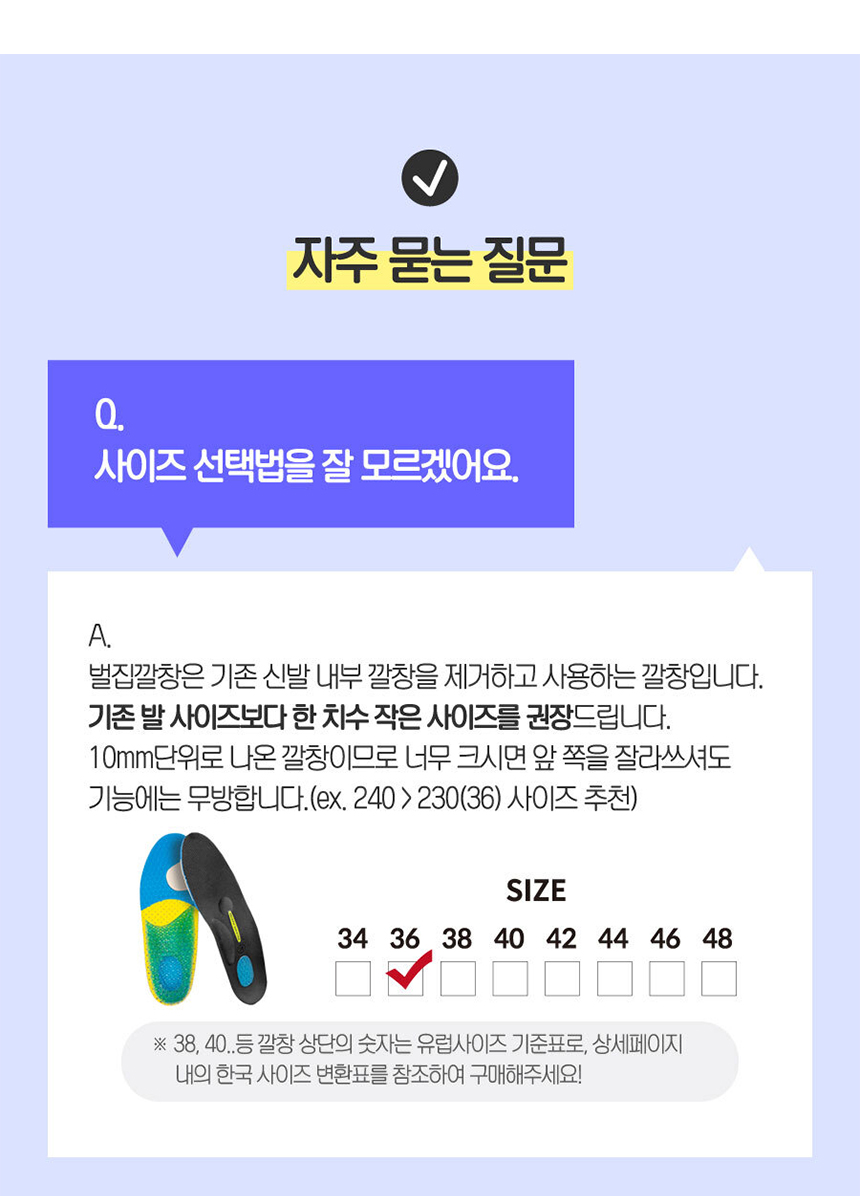
산돌폰트 문의 nin*** 2023.03.21 무슨 폰트 썼는지 확인 부탁드립니다! 댓글 0 등록 sta*** Asia 뉴굴림 같네요. https://www.asiafont.com/asfont/m_view.php?ps_db=sample&ps_boid=237&ps_page=4&ps_sele=&ps_ques=&ps_line=asc&ps_choi=&ps_divi= 장평값을 줘서 가로폭을 좀 줄인 것 같아요 2023-03-21 답글 달기 댓글 더보기 쉽고 빠르게 가장 비슷한 폰트를 알고 싶다면? 이미지로 검색하기
Asia 뉴굴림 같네요. https://www.asiafont.com/asfont/m_view.php?ps_db=sample&ps_boid=237&ps_page=4&ps_sele=&ps_ques=&ps_line=asc&ps_choi=&ps_divi= 장평값을 줘서 가로폭을 좀 줄인 것 같아요